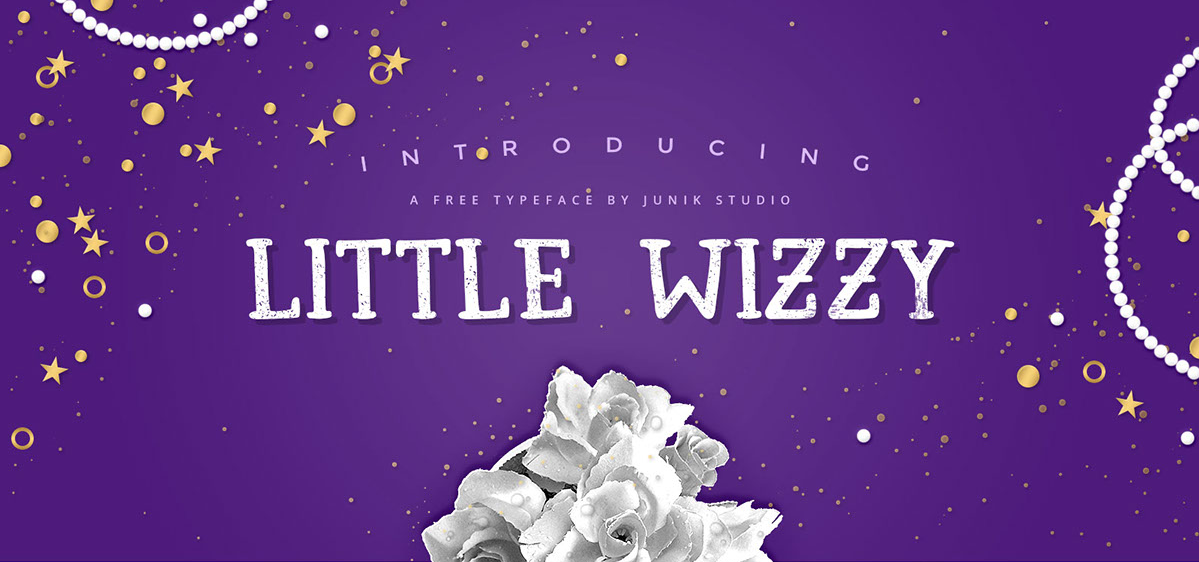
Little Wizzy Font – Download Grátis
A Little Wizzy Font é uma elegante fonte serif que traz um toque divertido ao design, especialmente adequada para criações mais formais ganharem um ar descontraído. Criação do designer Hamilton, essa fonte é perfeita para aqueles que buscam algo sofisticado mas também convidativo e amigável. Com seu estilo de serif claro e levemente arredondado, Little Wizzy oferece uma textura agradável e um toque de personalidade ao texto. Embora ofereça apenas caracteres básicos – letras, números e pontuação -, a Little Wizzy mantém o seu charme simplesmente envolvente. Ideal para uso em aplicações profissionais que buscam dar um jeito mais humano à escrita formal, ou como complemento em design gráfico que busca equilibrar elementos formais com uma leve dose de humor e descontração. Seja você designer de produtos digitais, ilustrador digital ou criativo digital, a Little Wizzy é certamente uma fonte para ser explorada.